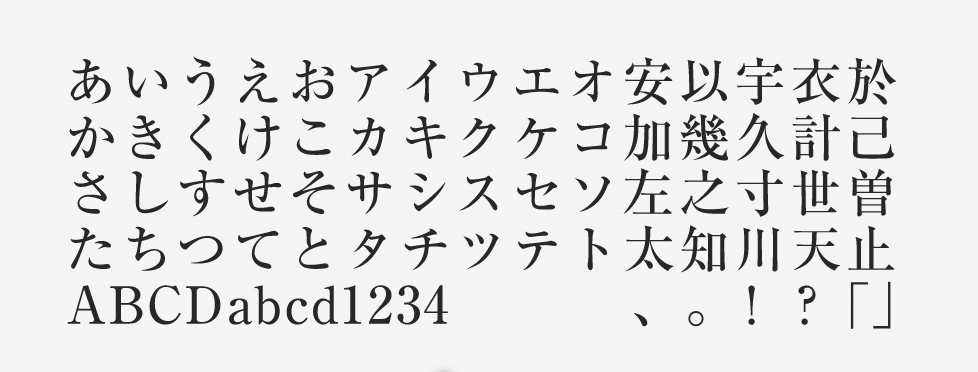
「リュウミン」について
森川龍文堂明朝体をベースに開発されたリュウミンは、モリサワの明朝体の中でも特に代表的なフォントです。1989年には、中ゴシックBBBとともにリュウミンL-KLが最初の日本語PostScriptプリンタに搭載されました。その後は、DTPを牽引するフォントとして活躍し、さまざまな場面で使用されています。
「リュウミン」の特徴
スタンダードな明朝体で、本文組みを中心に活用されており、見出しなどにも適しています。彫刻刀で彫った金属活字の名残で、左右のハライや点の形はシャープです。同時に縦画・横画の先端やウロコには柔らかさがあり、親しみやすい雰囲気も持ち合わせています。
雑誌など多くの商業印刷物で使われているため、馴染みのある書体であることも強みです。安定感があり、プロらしく仕上げるには「リュウミンを使えば間違いない」という頼れるフォントと言えるでしょう。
リュウミンは、信頼感、可読性、丁寧さ、真面目さを兼ね備えた安心の明朝体です。空気や水のように自然に文字を読ませたい時に有効なフォントの最高峰と言えるでしょう。ウエイトのバリエーションも多く、アルファベットもとても使いやすいです。